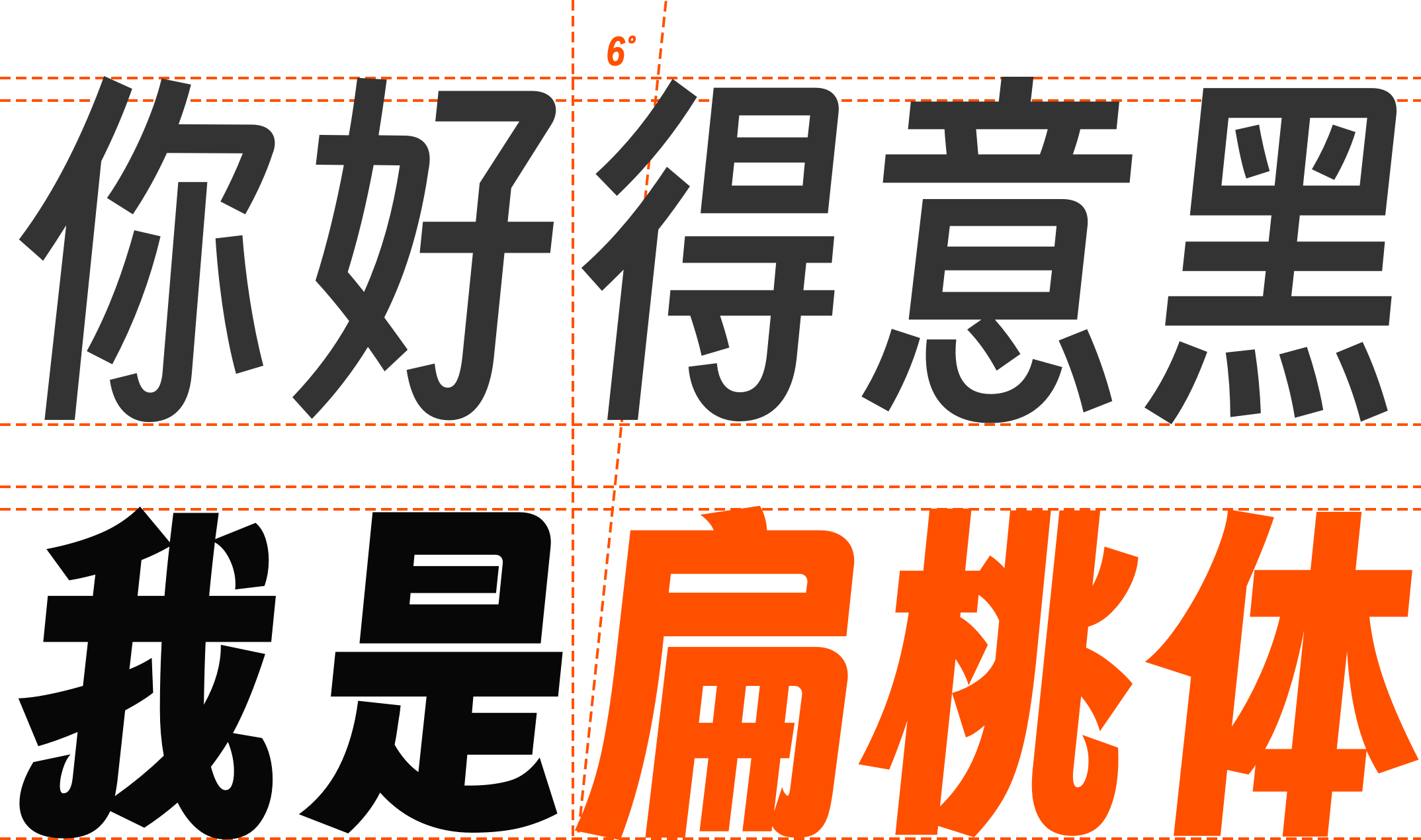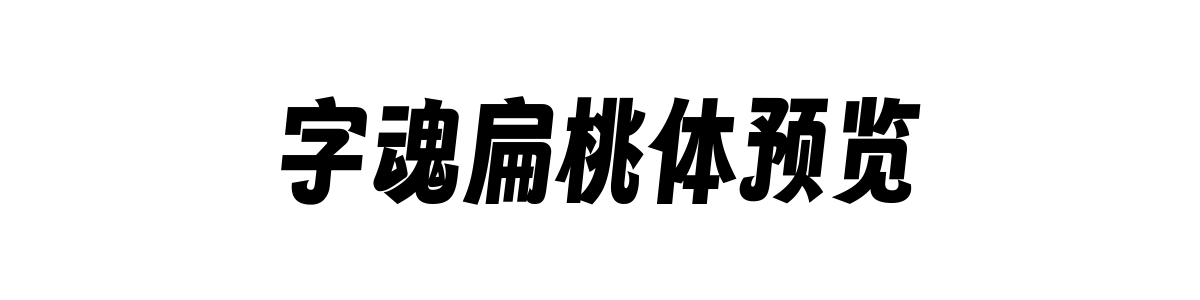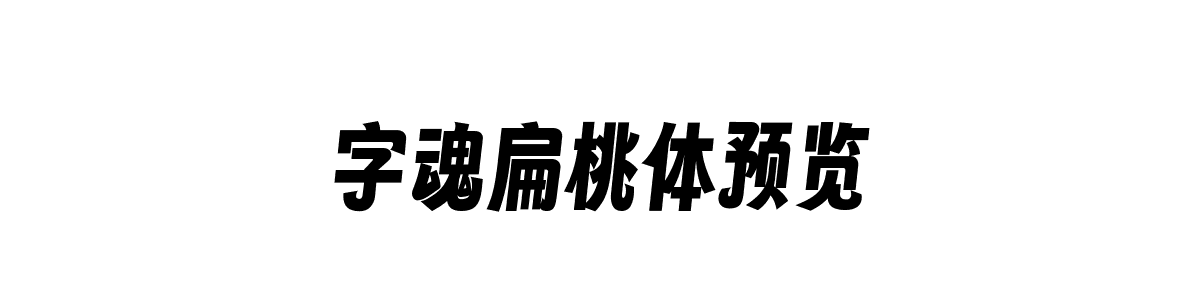
字魂扁桃体
字魂扁桃体(ZiHun BianTao Ti)是一款由字魂网基于开源字体得意黑进行二次创作后发布的免费商用字体。它在继承得意黑标志性风格的基础上,通过加粗字重、加宽字身及引入独特的“喇叭口”设计,打造出一款更具力度、重量感与鲜明个性的创意标题字体。
字体风格
字魂扁桃体的设计精髓在于其 “卷起来了”的喇叭口创意。该字体在得意黑6°到8°倾斜和高挑字身的框架上,对笔画末端进行了独特的卷曲处理,这一设计让标志性的微笑弧度演变为更具活力的视觉符号,使整个字体精神饱满、温和又时髦。
其风格在得意黑的潮流感之上,增添了更强的装饰性与趣味性。